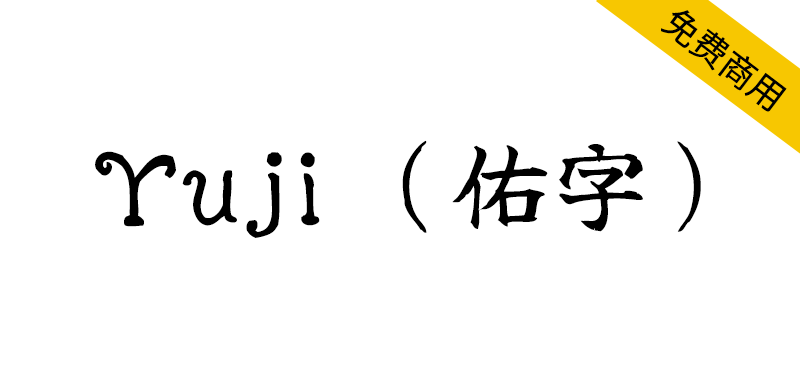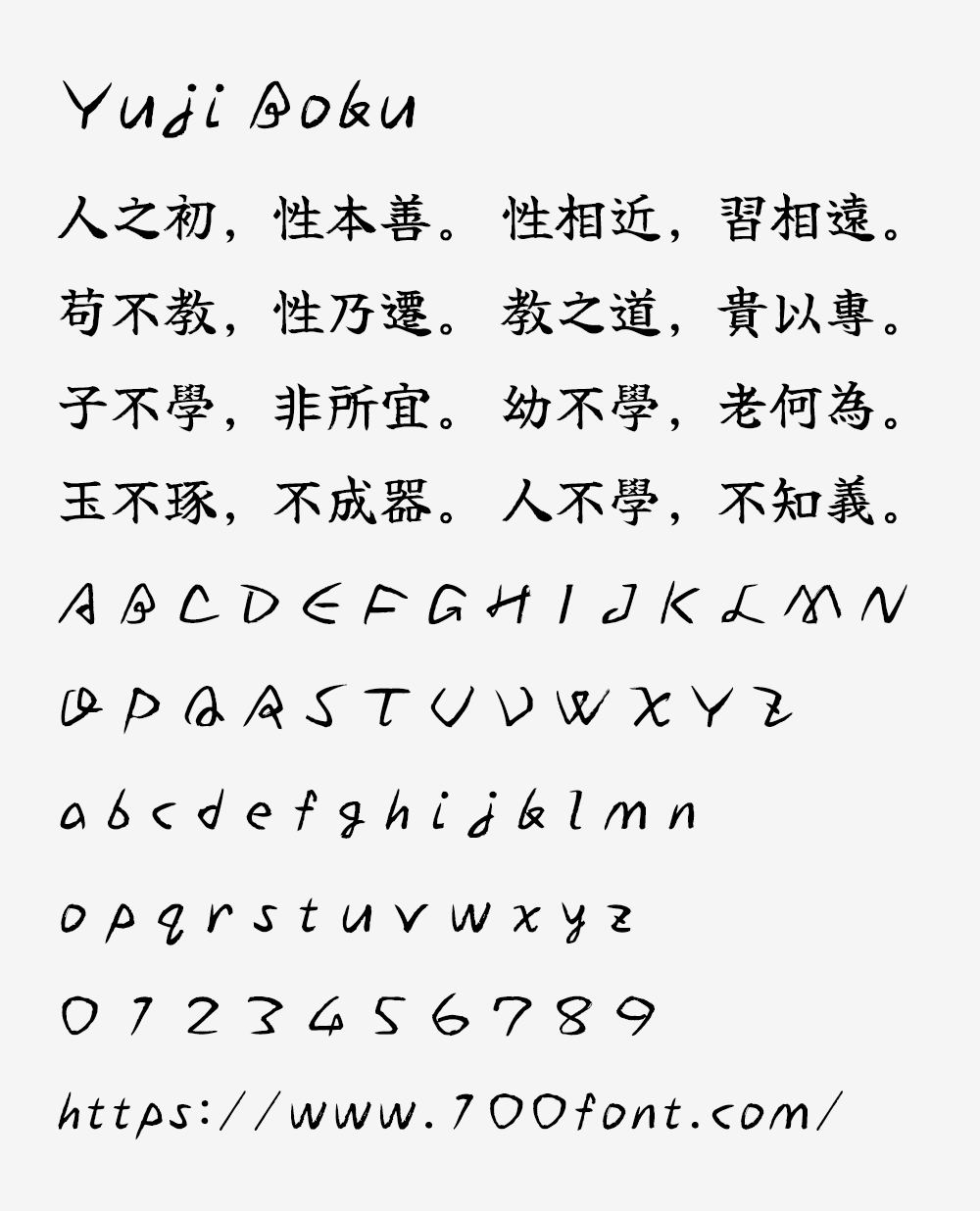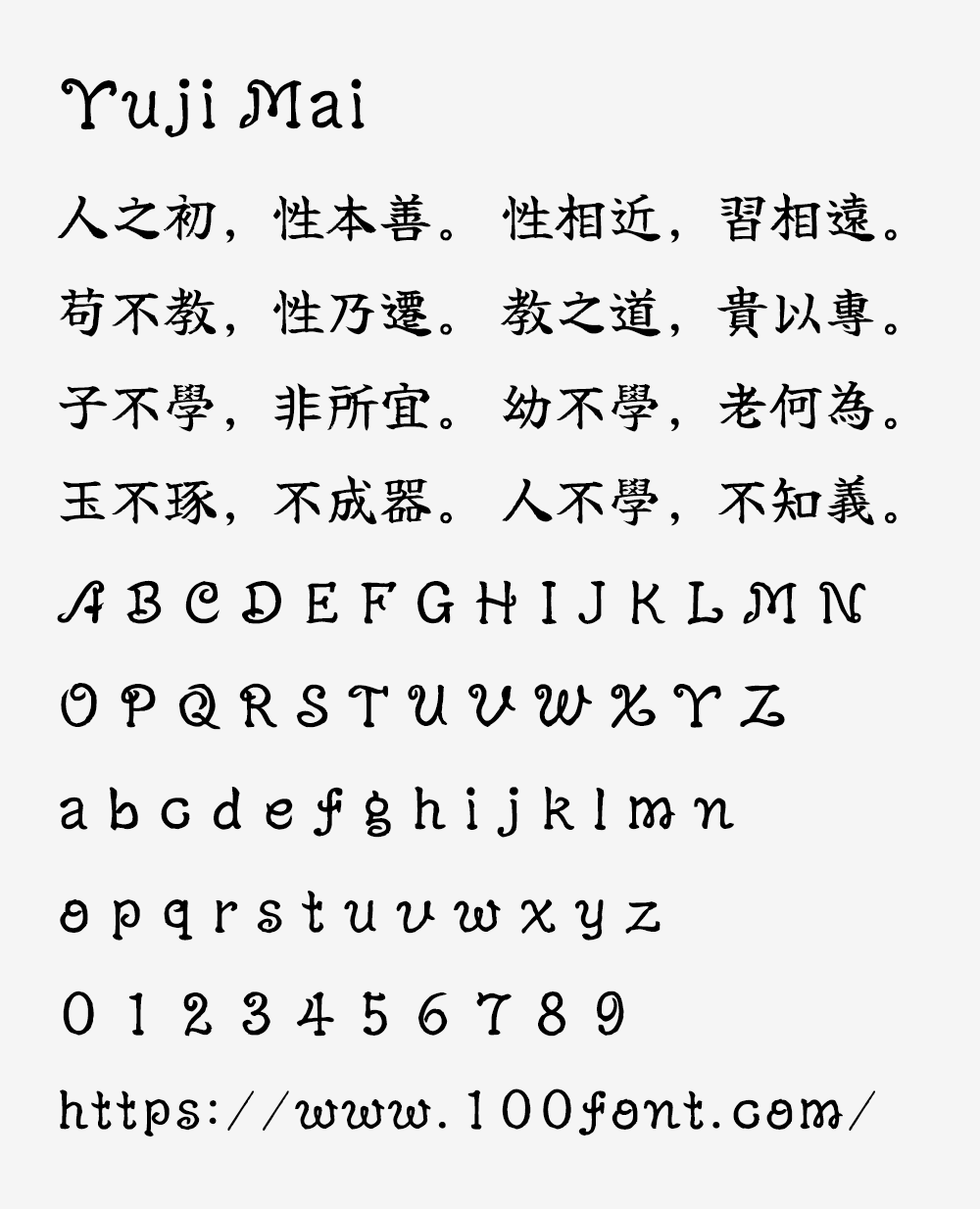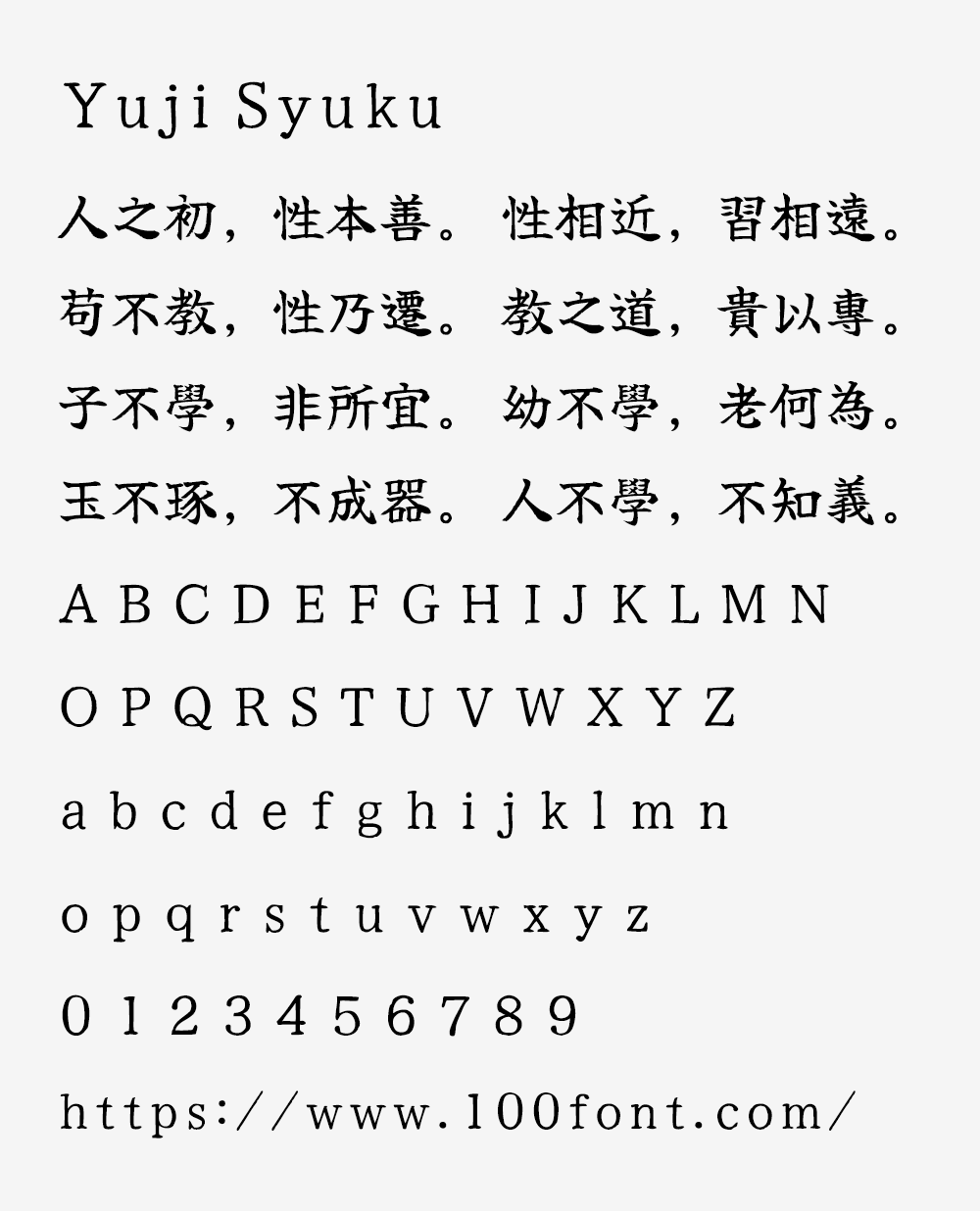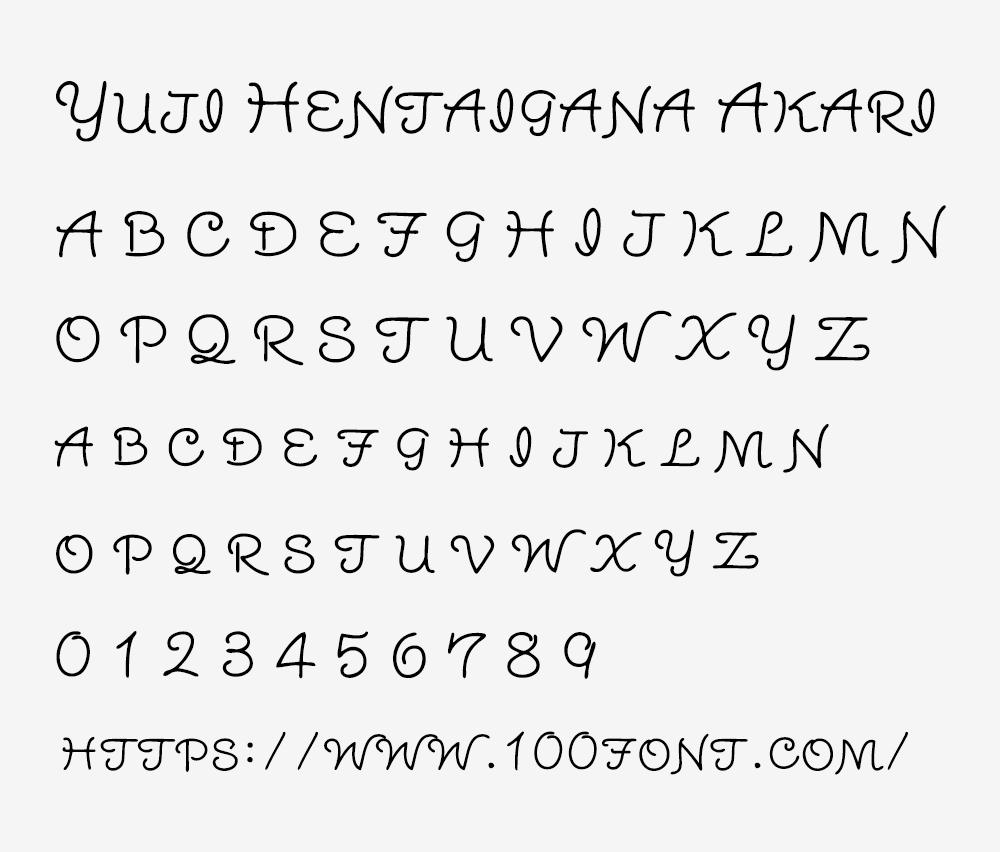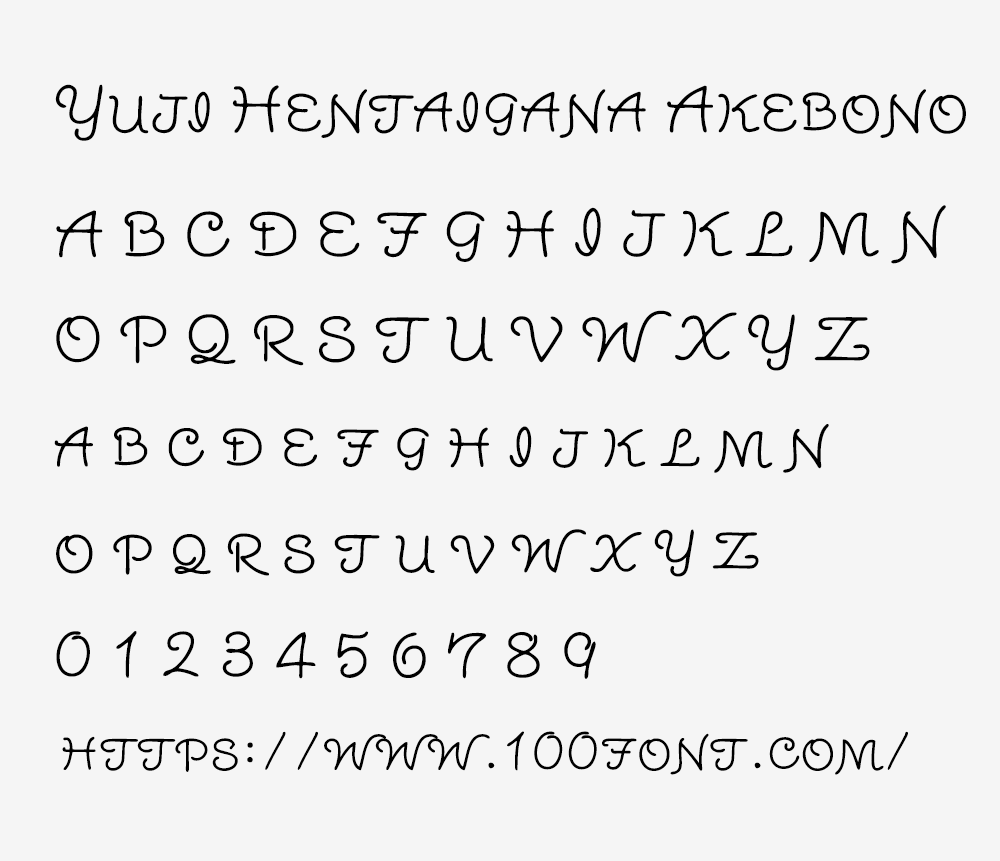
Yuji(佑字)系列包含有5种字体,设计上采用了日本书法家片冈裕司所写的原始字体,有3种不同类型的假名和2种不同类型的变体假名字体(Yuji Syuku、Yuji Mai、Yuji Boku这三款字体支持繁体、日文、英文;Yuji Hentaigana Akari、Yuji Hentaigana Akebono这两个属于英文字体,不支持繁体和日文)。
Yuji Syuku:它既有传统和尊严,又平易近人,这种设计能被大众广泛接受,汉字和一些符号与Yuji Mai、Yuji Boku相同。
Yuji Mai:它表达了一种自由、奔放、情感的美,拉丁字母是为了匹配假名笔划而写的。
Yuji Boku:这是一个新的和愉快的设计,它既简单又温暖。
Yuji Hentaigana Akari与Yuji Hentaigana Akebono:现在的平假名是在1900年被规定的,其余的字符,没有被选为平假名,被称为变体假名,变体假名有几种类型,Akari和Akebono是其中的两种,片假名不包括在变体假名中,拉丁字母被设计成大写字母,小写字母也是大写的。